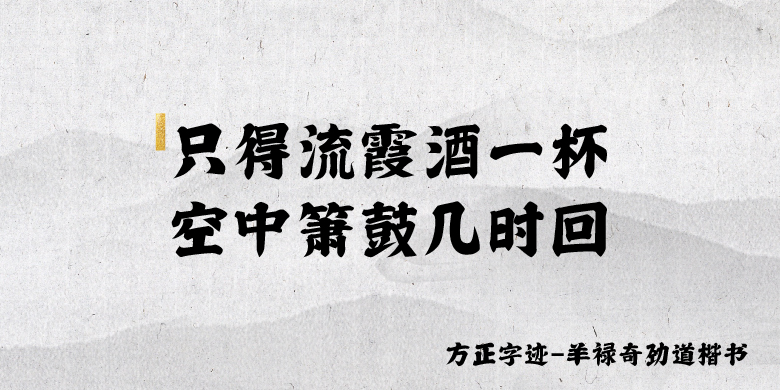
方正字迹-羊禄奇劲道楷书
字体品牌: 方正字迹 设计师:羊禄奇 字体分类:楷书、创意字体 字体属性:精品字 字符集:大陆简体(GB2312-80)、简繁扩展(GBK) 发布时间: 2021
羊禄奇劲道楷书笔画厚重刚劲、饱满遒劲,起笔转折处采用方圆结合,浑厚而灵动,尾笔处采用出锋,捺画亦借鉴了颜体的一波三折写法,刚柔并济,字体风格敦厚遒劲,饱满刚毅。此款字体适用于:海报、媒体、印刷广告、电影电视、报刊印刷等。
作者羊禄奇,曾在中学时获全国书法软笔类一等奖、大学校内获软硬笔书法一等奖。